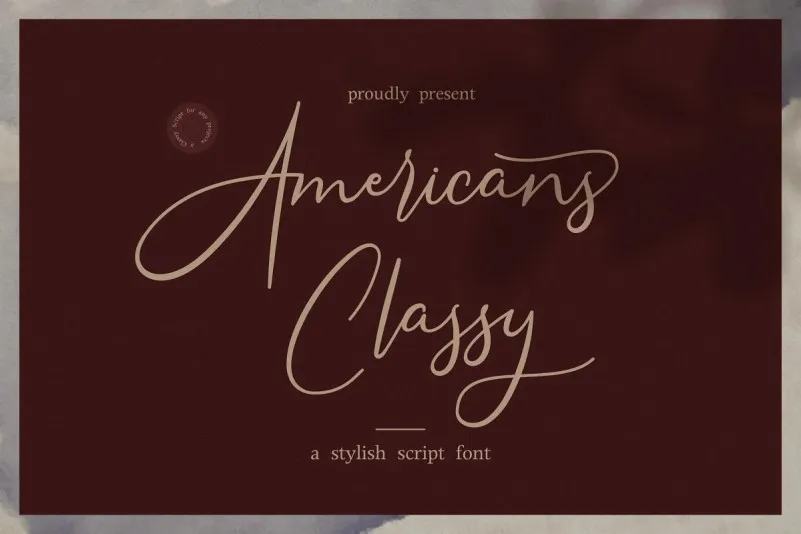
Esta font americana elegante é perfeitamente adaptada para projetos criativos que exigem um toque sofisticado e versátil. Com traços limpos e contrastes claros, esta tipografia script é ideal para aplicar como watermark em fotografias ou criar design de marca icônico, como logomarcas ou identidades visuais. Suas letras vibrantes e únicas são perfeitas para invitations, anúncios, designs de produtos, papelaria, designs de casamento e até mesmo etiquetas e embalagens de produto. Seja você um designer que busca adicionar uma pitada única a seus trabalhos ou alguém que está buscando uma maneira de tornar seu próximo projeto ainda mais especial e sofisticado, esta font americana elegante certamente será sua escolha ideal.